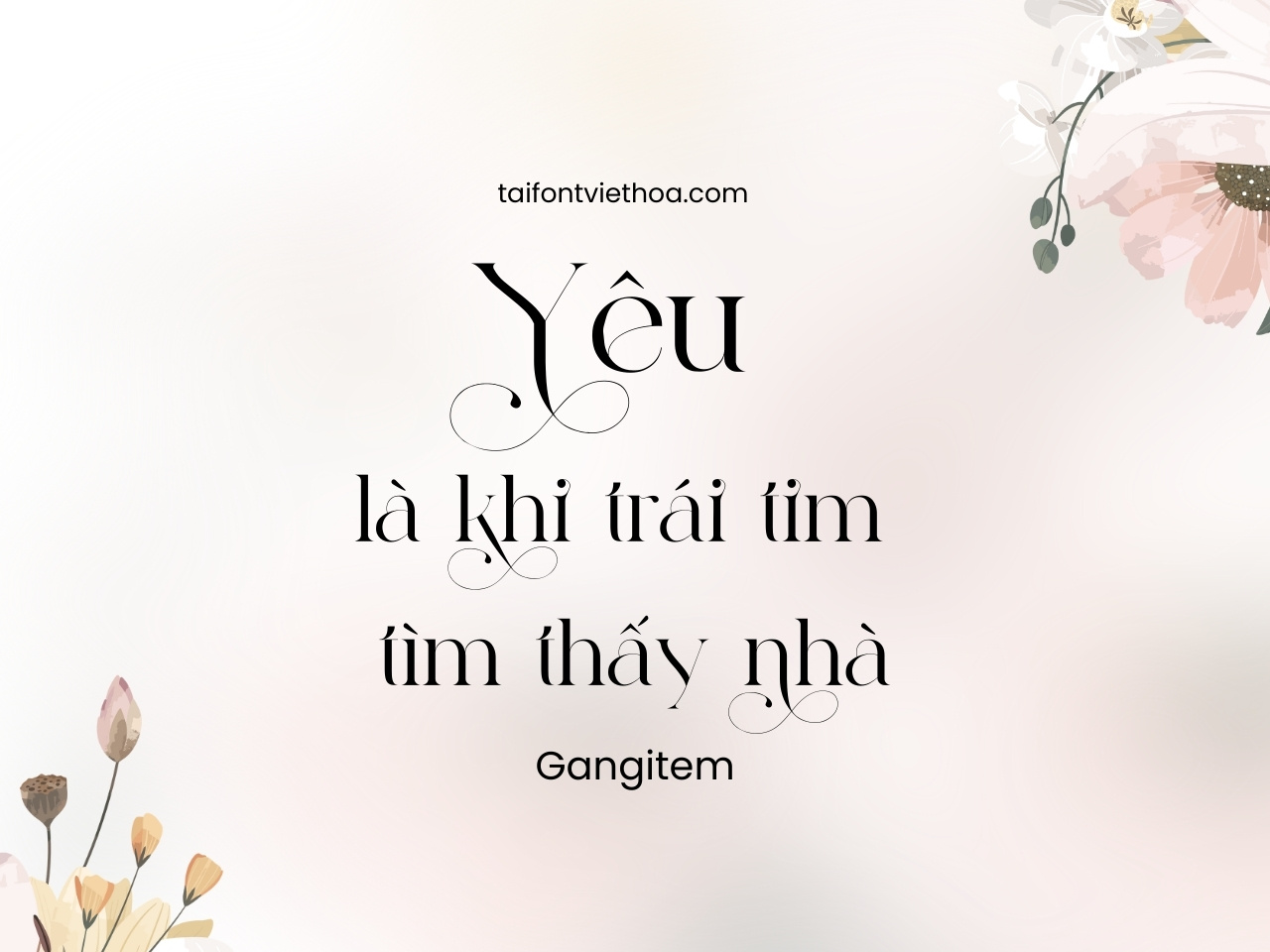
Giới thiệu font Gangitem – Phong cách serif sáng tạo từ 177Studio
Gangitem là một font chữ serif mang phong cách trang trí (decorative) với cấu trúc hiện đại kết hợp nét cổ điển duyên dáng. Được thiết kế bởi 177Studio – đơn vị chuyên tạo ra các bộ font có cá tính mạnh và hình dáng khác biệt, Gangitem thể hiện sự pha trộn hài hòa giữa nghệ thuật và hình học. Font được thiết kế để thu hút thị giác ngay từ những tiêu đề đầu tiên, giúp tăng độ nhận diện thương hiệu và tạo phong cách riêng cho các thiết kế sáng tạo. Phiên bản Việt hóa đã được hoàn thiện, hỗ trợ đầy đủ tiếng Việt cùng hơn 80 ngôn ngữ quốc tế khác. Font được taifontviethoa.com chọn lọc và chia sẻ như một giải pháp typography hoàn hảo cho các nhà thiết kế tìm kiếm chất riêng và sự khác biệt.
Đặc điểm độc đáo và ứng dụng của font Gangitem
Gangitem nổi bật với các chi tiết serif được cách điệu tinh xảo, các đường cong thanh lịch đan xen với khối hình học vững vàng, mang đến cảm giác vừa cổ điển, vừa phá cách. Font đặc biệt phù hợp cho tiêu đề, bìa sách, poster nghệ thuật, logo thời trang, bao bì mỹ phẩm cao cấp hoặc thiết kế sự kiện sang trọng. Phong cách của Gangitem thể hiện sự uyển chuyển, giàu tính biểu cảm nhưng vẫn đảm bảo khả năng đọc tốt ở kích thước lớn. Font lý tưởng cho các ngành như bất động sản, giáo dục, ẩm thực cao cấp, thời trang, ảnh cưới, hoặc các dịp lễ như Trung thu, Valentine, sinh nhật hay các sự kiện mang tính nghệ thuật cao.